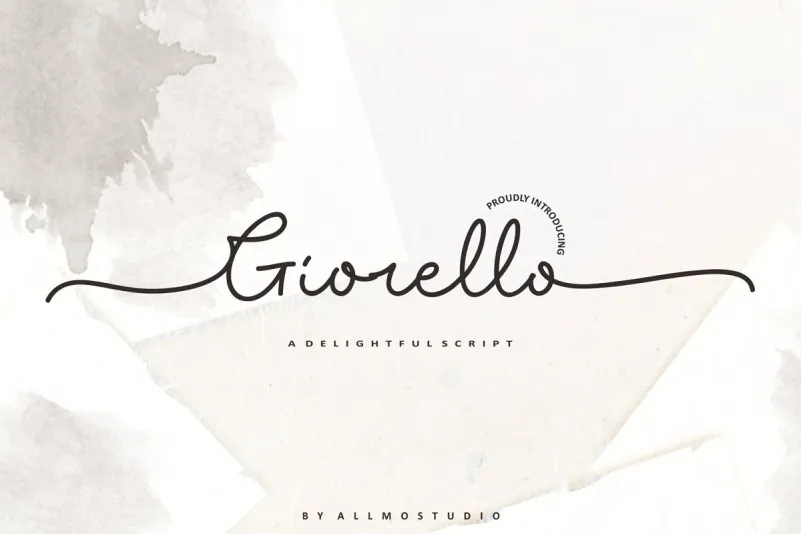
Giorello Signature Font – Download Grátis
A Giorello Signature Font é uma escolha excepcional para designers que buscam uma mistura única entre elegância e descontração. Desenvolvida pelo designer zziplex, essa fonte escrita à mão oferece um olhar único, adaptável tanto a estilos clássicos quanto modernos, garantindo que sua obra seja sempre original. Criada pela AllmoStudio, esta fonte traz nuances femininas e sofisticadas, projetada para adicionar um toque especial aos seus projetos. Ideal para marcas de moda, sites femininos ou boutique de casamentos, a Giorello Signature será sua melhor aliada para criar designs inovadores e modernos que valorizem a aparência sofisticada e desejável que você deseja transmitir. Esta fonte é perfeita tanto para aplicar em logotipos quanto na criação de headlines e posters, ou até mesmo nas embalagens dos seus produtos e convites de casamento.